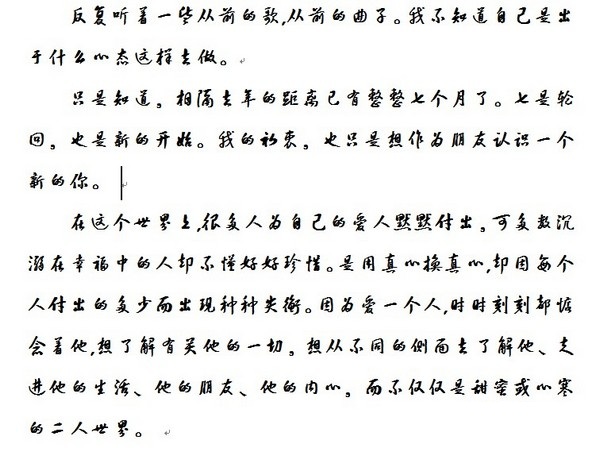
軟件介紹 軟件標簽: 字體 書法字體 超全40款鋼筆硬筆書法名家的字體基本上涵蓋了現代名家的字體,是龐中華字庫,喜歡字體的朋友趕快下載吧!效果圖:字體的使用方法:1.解壓后的字體文件復制到C:/windows/fonts2.下載文件–解壓后–復制–打開控制面板–字體–打開–粘貼。 軟件截圖 上一張下一張(1 / 1) 安裝詳細截圖 猜你喜歡 鋼筆字體 書法字體 鋼筆字體 鋼筆字體是設計領域經常用到的字體,鋼筆字體具有鮮明的個人特征,風格多樣,深受廣告設計、平面設計師的喜愛,除了一些手寫鋼筆字體,還有正楷、行書類的鋼筆字字體,為設計師們提供了豐富的字體形式,綠色資源網也有很多鋼筆字體下載和鋼筆字體包,需要的可以看一看 查看更多>> 鋼筆書法軟件手機版 93.56M/中文/10.0/v2.1.5 安卓版下載 鋼筆之家 4.83M/中文/10.0/v1.0.2 安卓版下載 鋼筆手寫字體免費 11.71M/中文/1.2/下載 鋼筆書法入門基知識 31.79M/中文/5.0/v6.3.1 安卓版下載 浮生體 1.92M/中文/5.0/下載 伯樂鋼筆行書字體 3.53M/中文/6.6/下載 書法字體 書法字體有哪些?主要包括了硬筆書法字體、英文書法字體和毛筆書法字體三大類,綠色資源網提供了多款好看的常用各種書法字體文件打包下載,如:李旭科書法字體、啟功書法字體等,趕快下載體驗吧! 查看更多>> 蔡云漢隸書書法字體ttf 2.61M/中文/10.0/下載 黃庭堅字體 2.39M/中文/6.6/下載 李旭科書法v1.4-中 3.59M/中文/7.7/下載 金梅書法豆豆 2.03M/中文/10.0/下載 金梅新海報書法 2.24M/中文/10.0/下載 劉夢吟書法行楷字體 3.66M/中文/10.0/下載 其他版本下載 標題 大小 更新日期 下載 下載地址 電腦版 鋼筆書法字體 超全40款 點擊報錯 軟件無法下載或下載后無法使用,請點擊報錯,謝謝! 關閉報錯反饋 請描述您所遇到的錯誤,我們將盡快予以修正,謝謝! *必填項,請輸入內容 本類最新 首爾南山體字體 v1.06 官方版 潮字社風云簡ttf 潮字社凌渡鯤鵬簡體字體 潮字社曾玉波手書簡字體 微博慧心字體 阿里巴巴iconfont字體庫 相關文章 Windows 7系統(tǒng)默認字體還原技巧 Photoshop字體安裝使用方法和技巧 綠色資源網教你谷歌瀏覽器怎么調節(jié)字體大小 Mac下如何安裝字體?蘋果Mac系統(tǒng)安裝字體的三種方法 photoshop 缺少字體對照表(中英對照表)_字體中英文對照表大全 CDR字體列表缺少字體的解決方法 用戶評論 熱門評論 最新評論 發(fā)表評論 查看所有評論(0) 昵稱: 請不要評論無意義或臟話,我們所有評論會有人工審核. 字數: 0/500 (您的評論需要經過審核才能顯示)